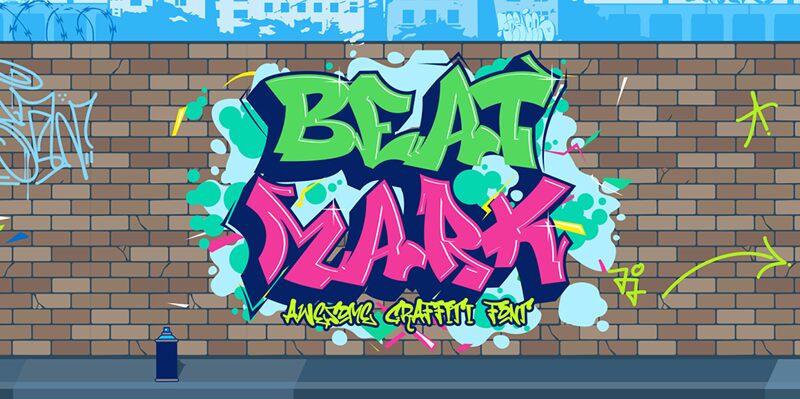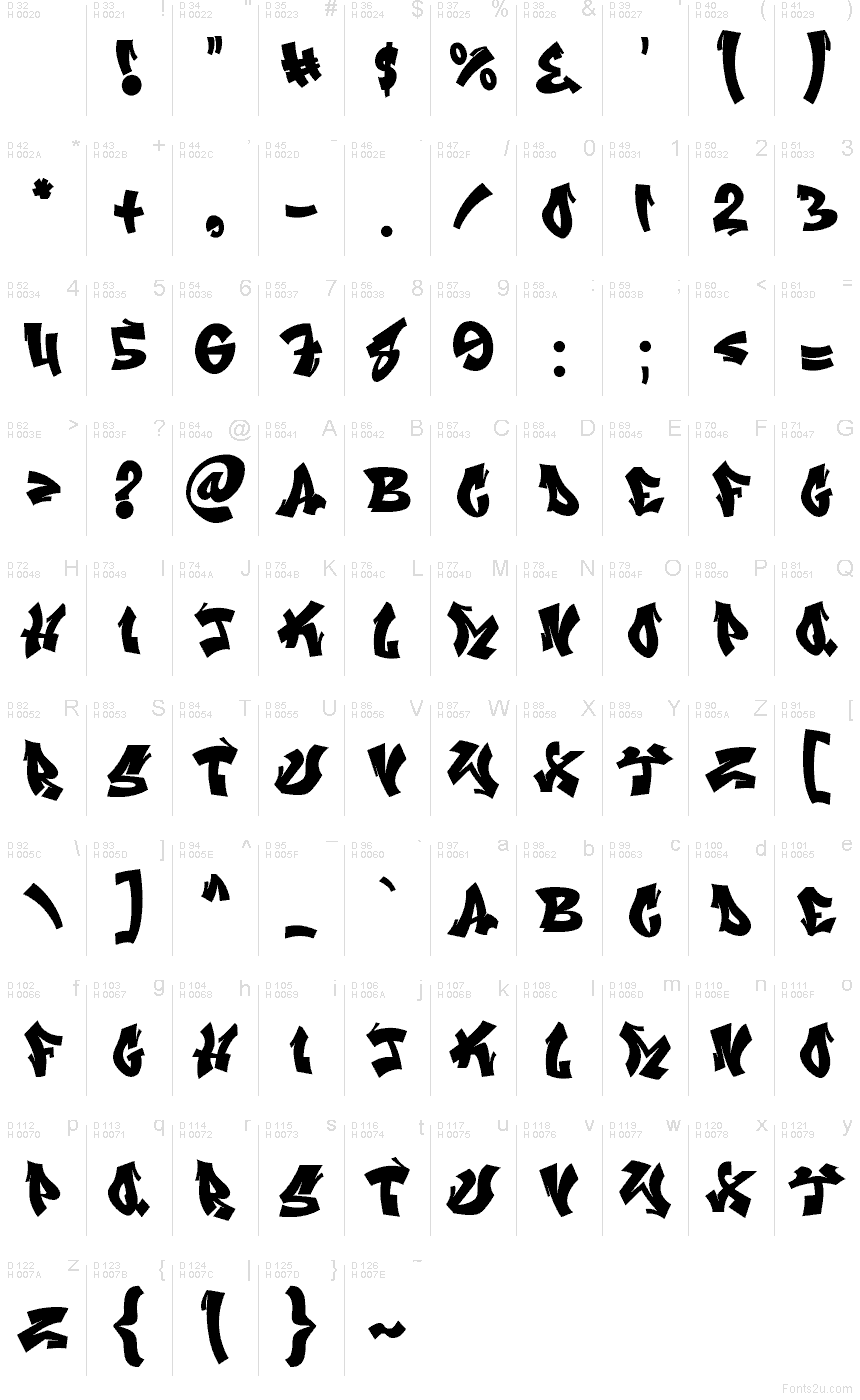
Beat Mark
Beat Mark od Sipanji x Figuree je bezplatné graffiti písmo poháněné zubatými siluetami, sekanými rohy a náhlými diagonálními řezy, díky nimž písmena působí, jako by byla vyříznuta z černého papíru. Tento neklidný obrys vytváří nerovnoměrný a hlasitý rytmus s ostrými vrcholy a hákovitými konci, které připomínají spíše ručně psané street tagy než uhlazené dekorativní písmo.
Plakáty, obaly hudebních alb, skate grafika, letáky na akce a branding streetwearu jsou pro toto písmo ideální, zejména pokud chcete, aby krátká slova měla okamžitý vizuální dopad. Zlomený obrys a nakloněný pohyb dodávají návrhům log a záhlavím na sociálních sítích syrovou, „ulicí poznamenanou“ energii, která by byla pro neutrální branding příliš agresivní.